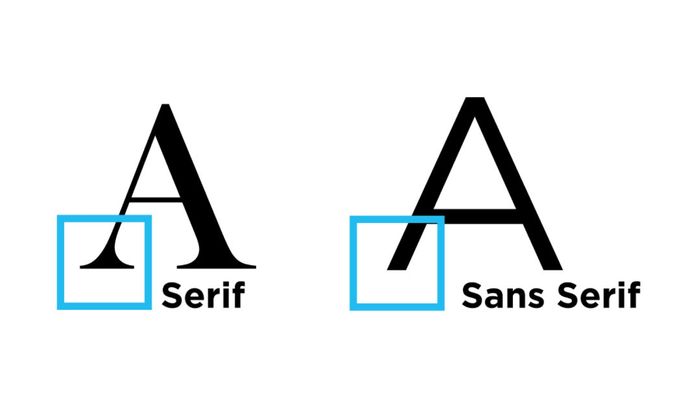
Font libro messa
Mi sposerò il 21 giugno e al momento sono alle prese con il libretto messa. Io farò la copertina su Canva e il testo in Word e volevo chiedervi delle informazioni.
Che font avete usato per il Word ? Che grandezza avete usato?
Essendo che sicuramente sarà un A5 la grandezza migliore é 12 e il font che si legge meglio e il più usato é Arial (che fa parte della famiglia dei sans serif, sono caratteri più semplici come anche un Helvetica)
Poi puoi osare di più per i titoli e caso mai mettere un font diverso e più grande anche 14 punti usando un Time new roman (serif)
Foto per capire 😊Font libro messa 1
Il libretto di matrimonio sarà in formato A5..
Il formato del nostro libretto era 12x17, lo volevo piccolo in modo che potessero metterlo anche in borsetta volendo. Per questo il carattere 12 che di solito uso mi sembrava troppo grande, quindi ho usato un 10. Il carattere era Georgia…. Assomiglia abbastanza ad uno stampato.
In genere io uso per tutto il carattere 12 di Times new roman.
Noi abbiamo fatto grandezza 12 il font non lo ricordo